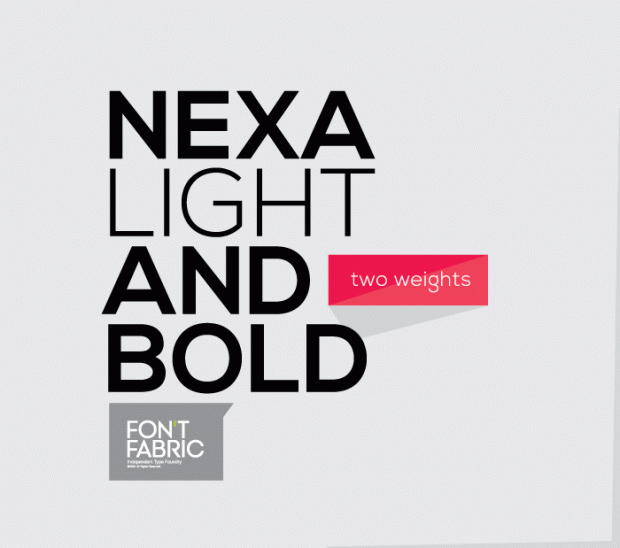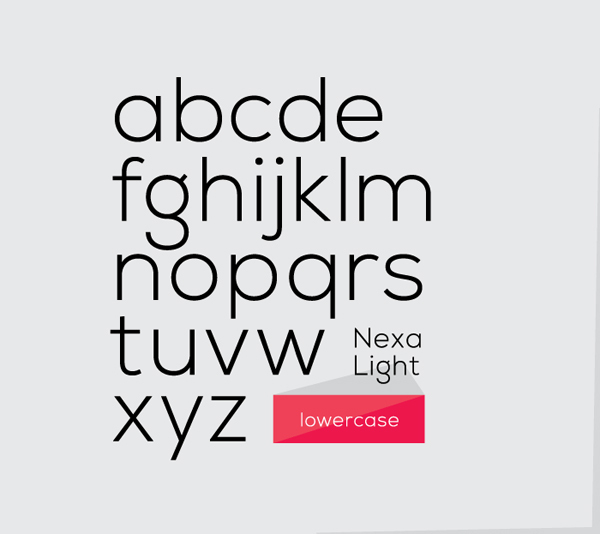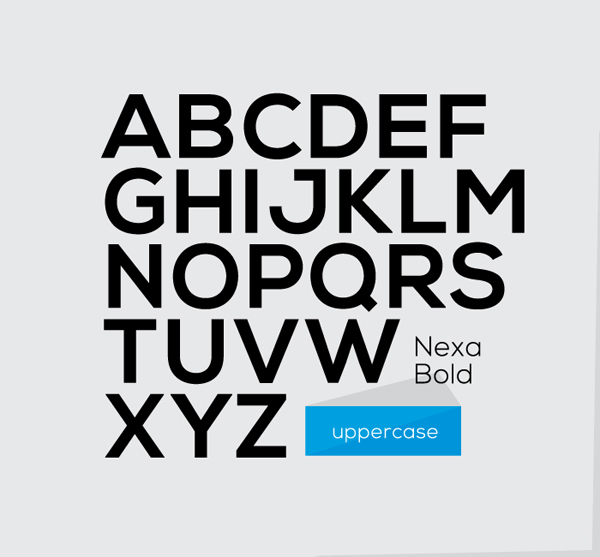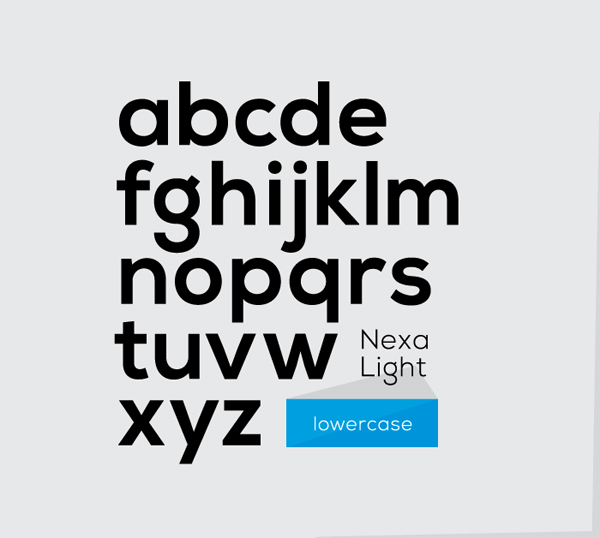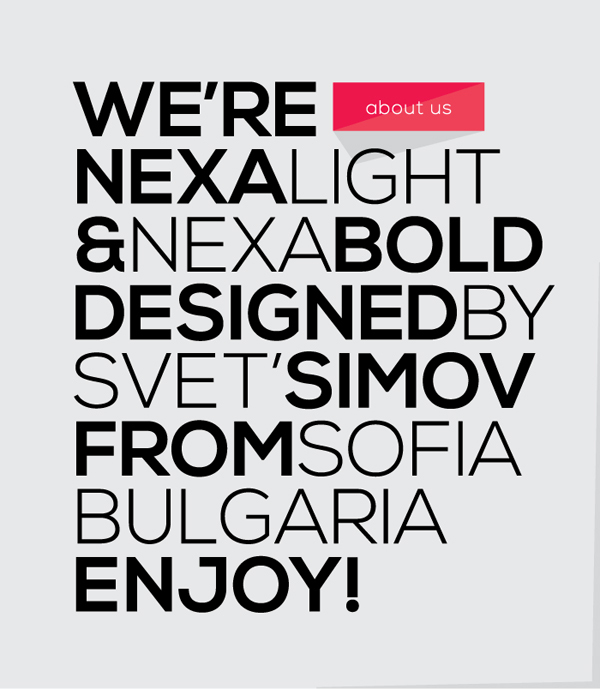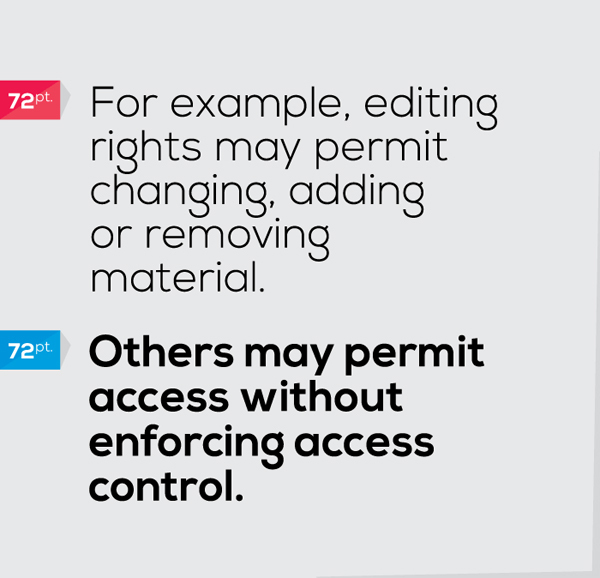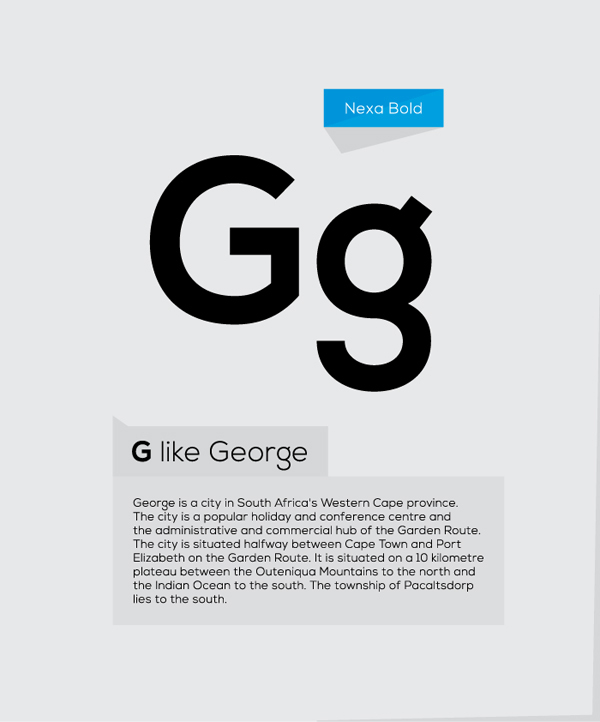
En tant que webdesigner, on a toujours besoin de typographie, en voila une tout a fait symptique qui vous permettra de faire des créations tip top. Typographie NEXA est une Free Font créée par Fontfabric.